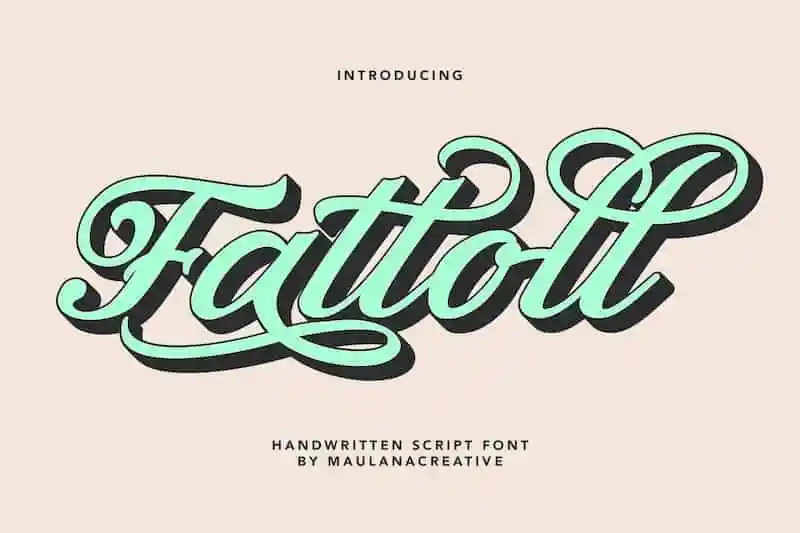
Fattoll Script Font – Download Grátis
A Fattoll Script é uma elegante fonte em script que oferece muitas alternativas círconflexivas e swashes, criando um estilo único e sofisticado. Ela foi projetada e compartilhada pelo Maulana Creative. Esta fonte se destaca para aplicações como design de identidade corporativa, postagem de mídia social, selos ou até mesmo estampas de casamento. Estando disponível em uma ampla gama de usos, a Fattoll pode transformar seus projetos e torná-los ainda mais chamativos. Seja para um projeto de marca inovador ou um site especializado no design gráfico, a Fattoll tem o poder de destacá-lo dos demais.